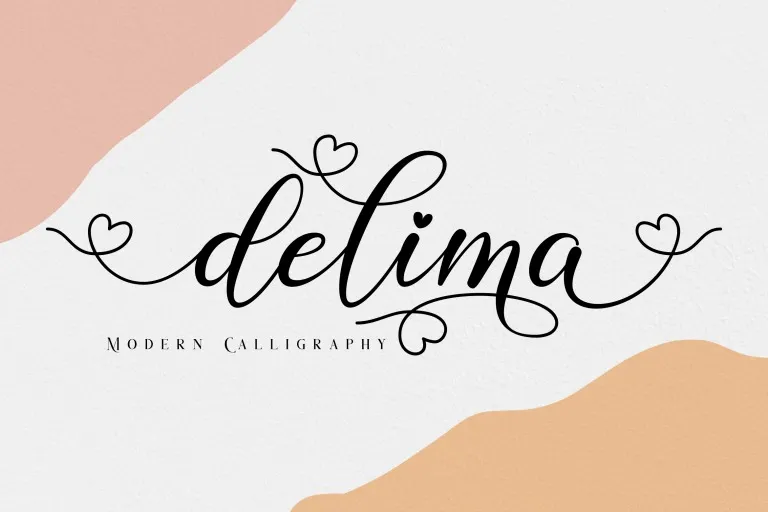
A Delima é uma elegante tipografia com traços que dançam sobre a linha base do papel. Essa fonte romântica e suave é perfeita para todas as suas necessidades de design, desde criação de logomarcas e identidade visual até capas de livros, postais casuais e convites de casamento. Delima também se destaca como uma ótima escolha para projetos que envolvem mensagens pessoais, como cartões de cumprimentos e citações. Seja você um designer profissional ou um amante da arte digitizada, a Delima oferece um toque suave e sofisticado aos seus trabalhos. Sempre que precisar de uma fonte romântica e suavemente elegante para seus projetos de design, a Delima não apenas atende às suas expectativas, mas supera-as.